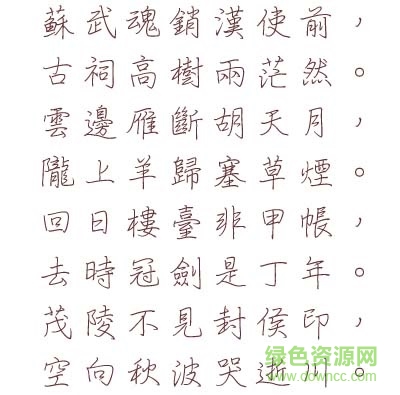
文鼎細(xì)鋼筆行楷字體適用于廣告設(shè)計(jì)、出版印刷、商業(yè)用字等多種不同領(lǐng)域,還可以讓喜歡鋼筆字的用戶參照練習(xí),這款字體美觀大方,有需要的用戶趕快來本站免費(fèi)下載體驗(yàn)吧!
文鼎細(xì)鋼筆行楷字體是一款筆畫比較細(xì)的鋼筆字體,給人的感覺非常流暢,適合大家對(duì)照練習(xí)鋼筆字。